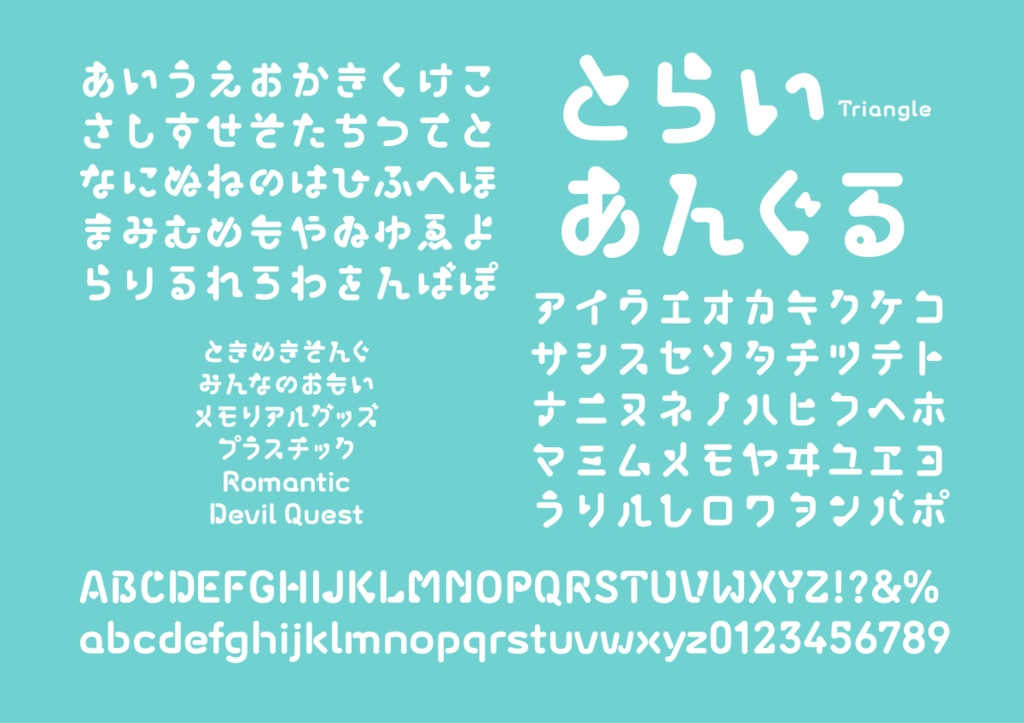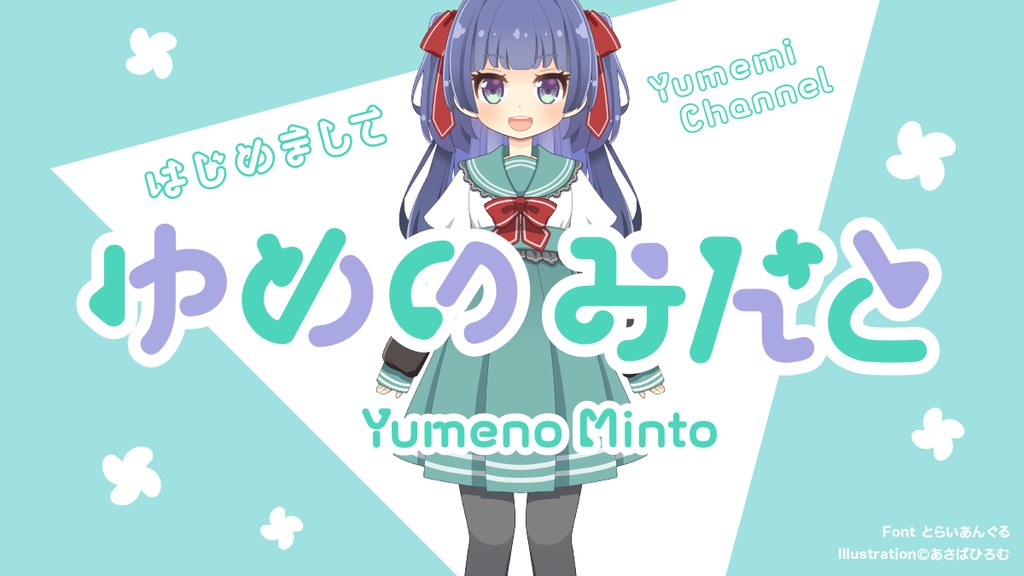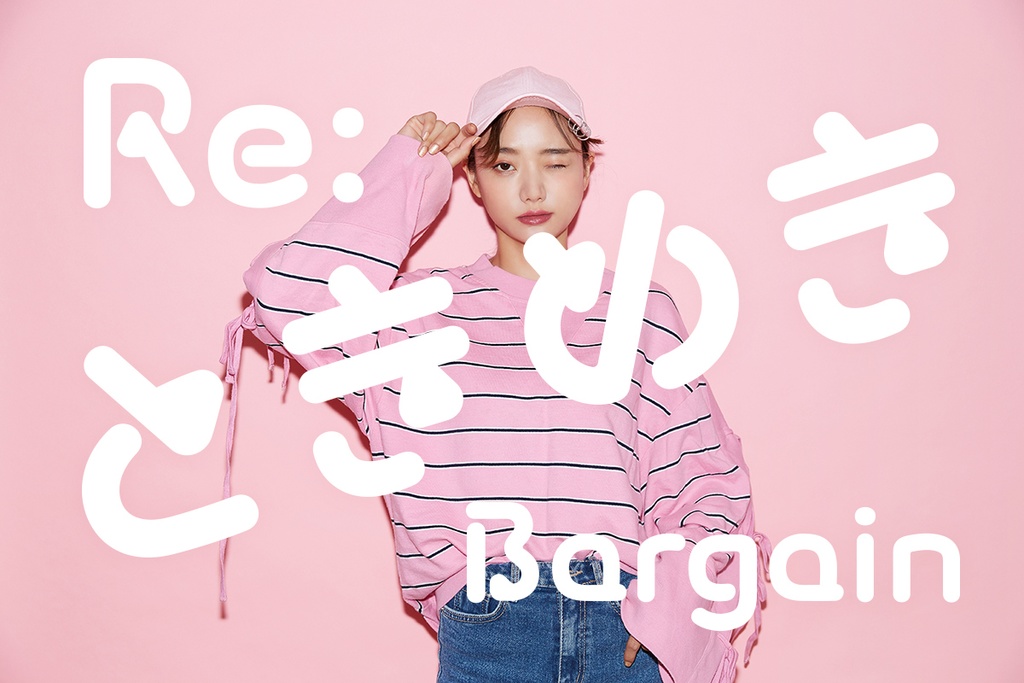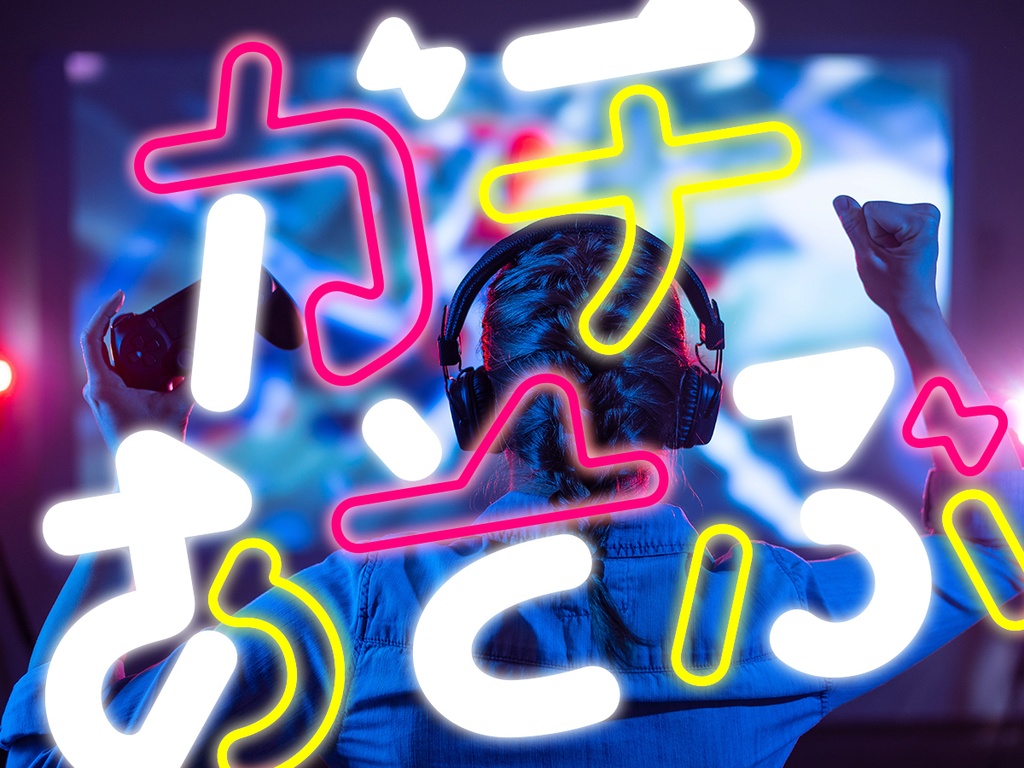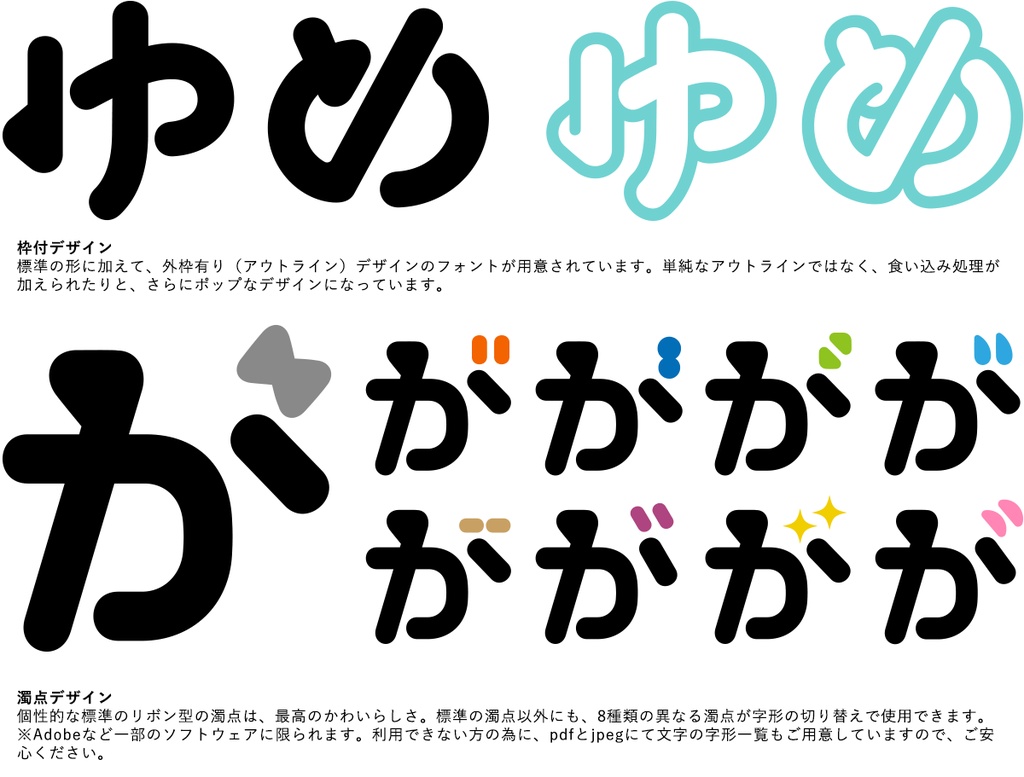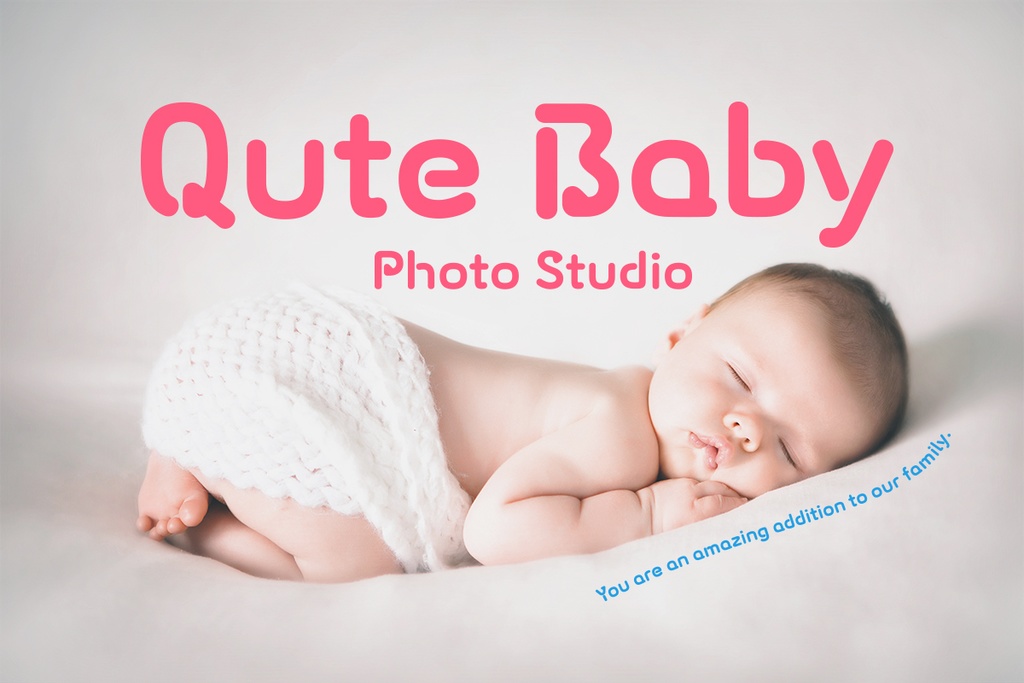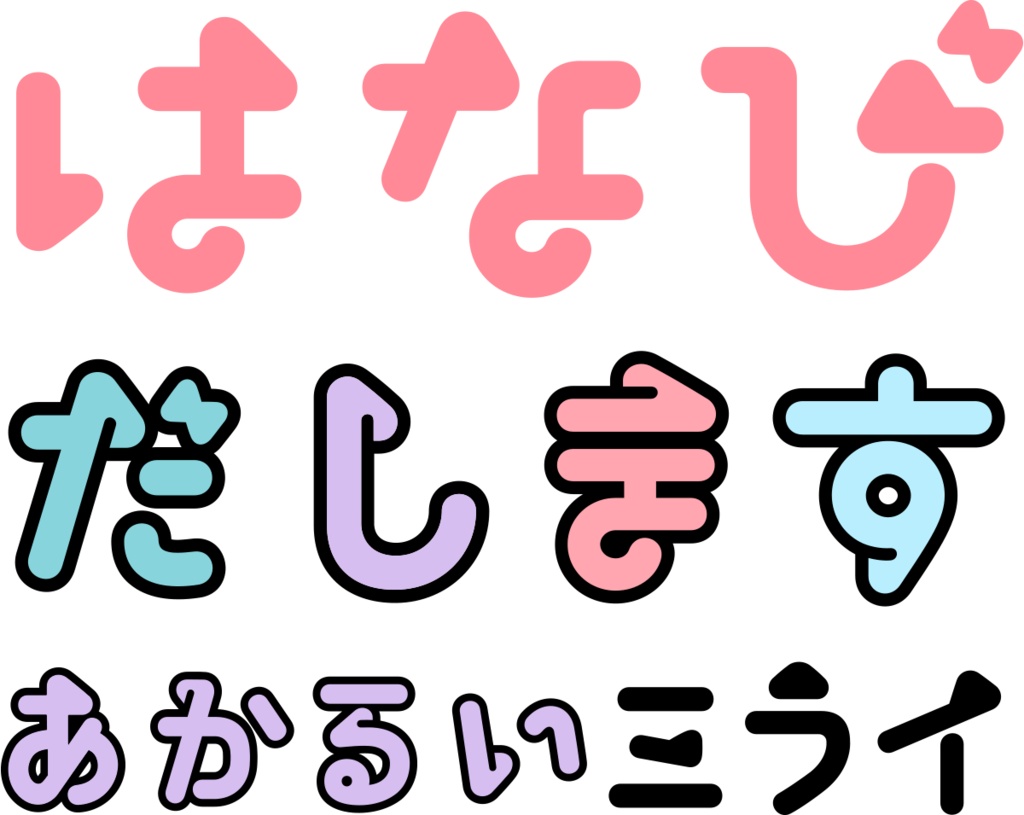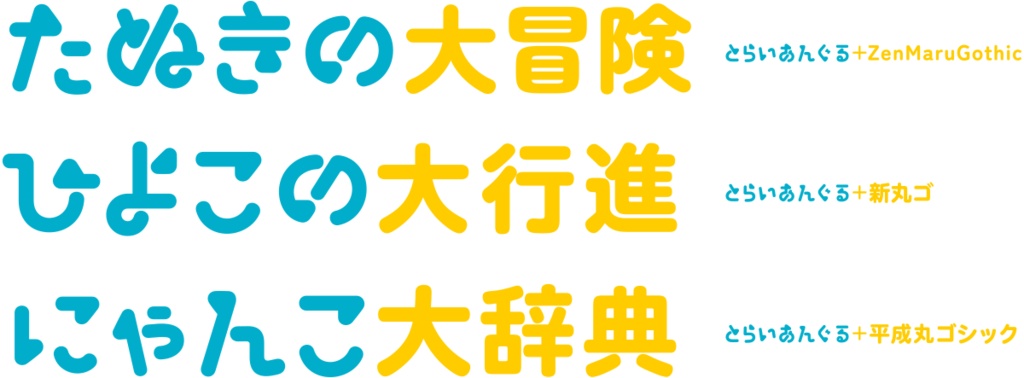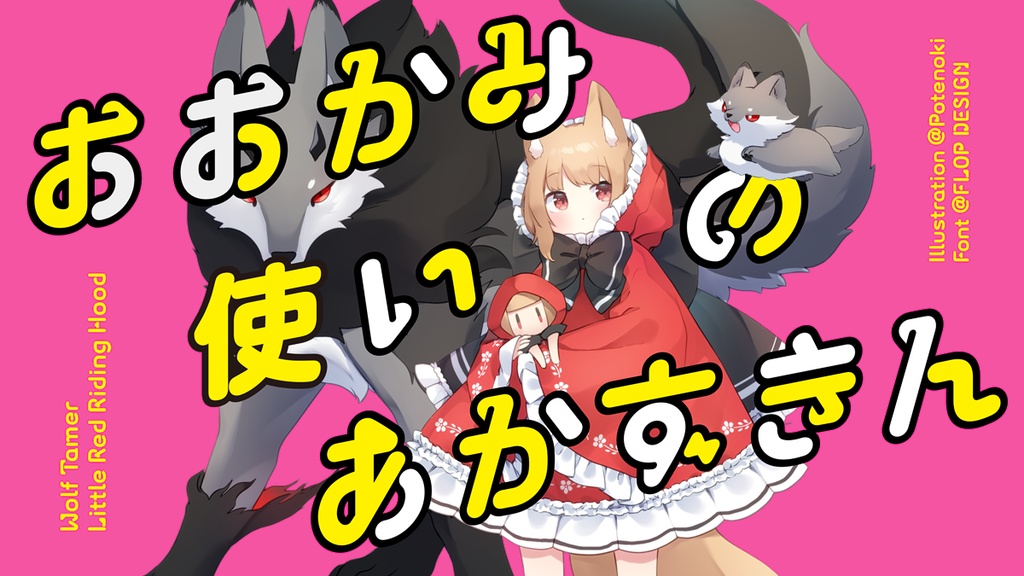
とらいあんぐるフォント(2フォントset)
三角形の形が印象的なロゴ向けのキュートな丸ゴシック体。文字の切れ方とつながり方がとてもポップで、使うだけで楽しいデザインが生まれます。懐かしさと未来感のふたつの要素のあるレトロフューチャーな世界観は唯一無二。動画サイトへの文字入れ、漫画への使用なども大活躍。 ■動作環境 Mac:システム/OS X対応(10.x)〜最新のOS X Windows:OS/日本語版Windows2000、XP、VISTA、Windows7〜11以降 フォント形式:OpenTypeフォント 1商品(1ライセンス)につき1ユーザー1PCのみがご利用いただけます。複数人で使用する場合は人数分をご購入ください。 ■収録文字について とらいあんぐる収録文字数785字。とらいあんぐるoutline収録文字数389字。※収録文字はアルファベット、ひらがな、カタカナ、約物の一部。 ■安心して使えるロイヤリティフリーの書体 あらゆる商用・デザイン用途(印刷物・ゲーム・アプリ・映像・動画・ロゴ・同人作品)に使用できる、商用申請の必要のないロイヤリティフリーの書体になります。文字の加工・変形も可能です。ご安心ください。 ■枠付デザイン 標準の形に加えて、外枠有り(アウトライン)デザインのフォントが用意されています。単純なアウトラインではなく、食い込み処理が加えられたりと、さらにポップなデザインになっています。 ■濁点デザイン 個性的な標準のリボン型の濁点は、最高のかわいらしさ。標準の濁点以外にも、8種類の異なる濁点が字形の切り替えで使用できます。※Adobeなど一部のソフトウェアに限られます。利用できない方の為に、pdfとjpegにて文字の字形一覧もご用意していますので、ご安心ください。 ■OpenType機能 詰め組み機能 ペアカーニング(仮名・プロポーショナル欧文) 字形切り替え機能(1つの文字で異なる字形を用意しています) ■収録フォント とらいあんぐる、とらいあんぐるoutline